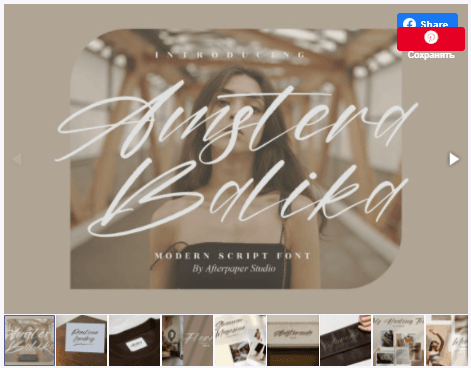
Amstera Balika Font
Amstera Balika — это шикарный, утонченный рукописный шрифт, излучающий изысканность и элегантность. Благодаря стильным альтернативам и лигатурам этот шрифт идеально подходит для любого проекта.